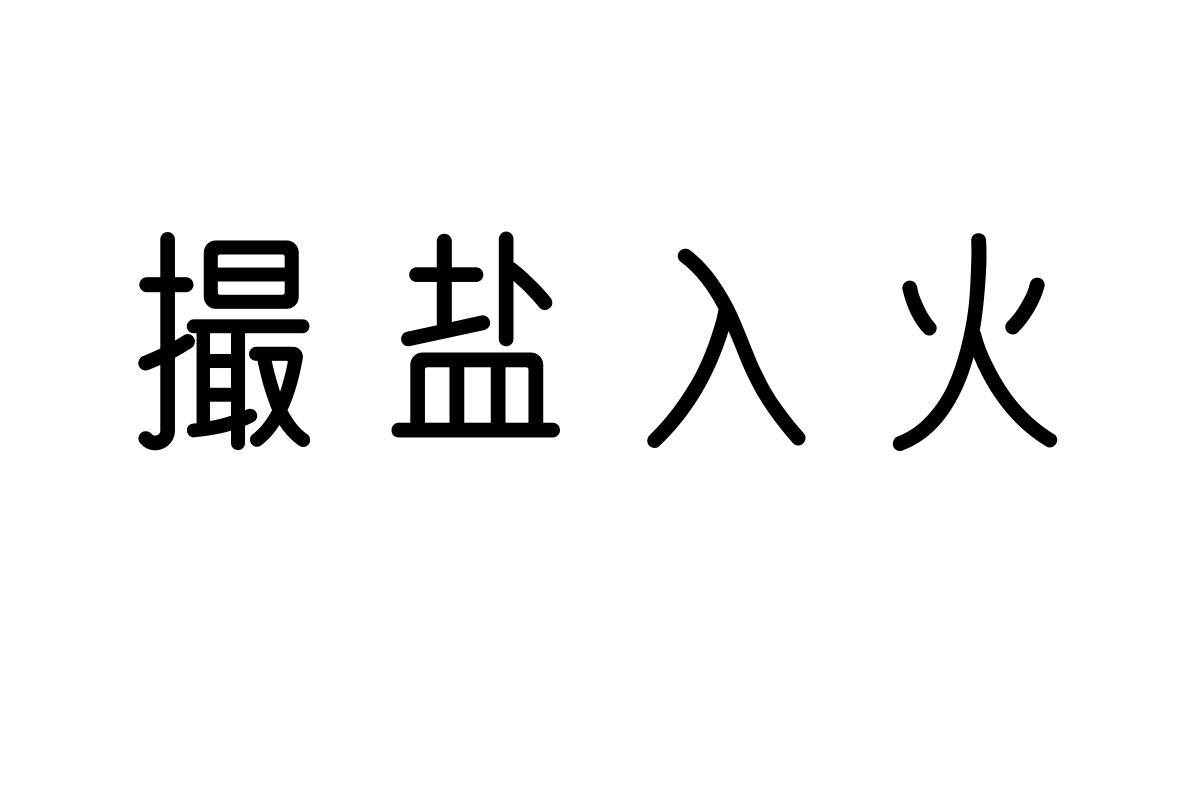
文道雅圆体是一款具有独特风格的中文字体,它以其圆润的字形和流畅的笔画而受到广泛赞誉。这款字体的设计灵感来源于中国古典文化中的书法艺术,因此它在视觉上给人一种优雅而庄重的感觉。
文道雅圆体的特点包括:
1. 字形圆润:这款字体的字形呈现出一种柔和而饱满的感觉,给人一种亲切而温馨的印象。
2. 笔画流畅:文道雅圆体的笔画线条流畅自然,没有生硬的棱角,使得整个字体看起来更加和谐。
3. 风格独特:这款字体融合了传统与现代的元素,既有古典韵味又不失时尚感,适合用于各种商业和设计场合。
4. 易于识别:文道雅圆体的字形简洁明了,即使在小尺寸下也能保持可读性,非常适合于印刷和数字媒体的使用。
总之,文道雅圆体是一款具有独特魅力的中文字体,它以其圆润的字形、流畅的笔画和独特的设计风格,为设计师们提供了丰富的选择。无论是用于品牌标识、海报设计还是网页布局,文道雅圆体都能展现出其独特的美感和实用性。